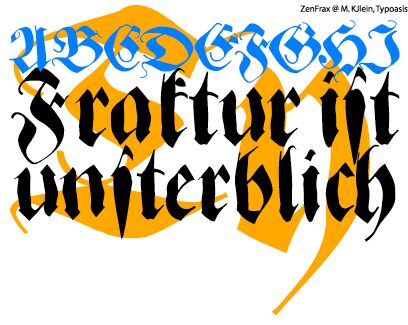
Zen Frax Freestyle von M. Klein ist eine kostenlose mittelalterliche Blackletter-Schrift mit einer feierlichen, raumgreifenden Ausstrahlung. Die Buchstaben orientieren sich an klassischen gotischen Winkeln und gebrochenen Kurven. Der eigentliche Clou sind jedoch die geschwungenen Verzierungen: hakenförmige Anfänge, bandartige Bögen und lange Ausläufer verleihen den Großbuchstaben einen heraldischen Charakter, der eher für prächtige Titel als für normalen Fließtext gemacht ist.
Sie passt perfekt zu Plakaten, Album-Titeln, Buchcovern, Event-Flyern und Branding-Projekten, die einen liturgischen, nostalgischen Akzent setzen möchten. Da es sich um eine kostenlose Schrift handelt, kommt sie in kurzen Phrasen am besten zur Geltung, wo die geschwungenen Linien Raum zum Atmen haben. Verwenden Sie sie für Titel, Kapitelanfänge oder Initialen, wenn Sie dramatische Akzente setzen möchten, ohne die Blackletter-Tradition zu verlassen.